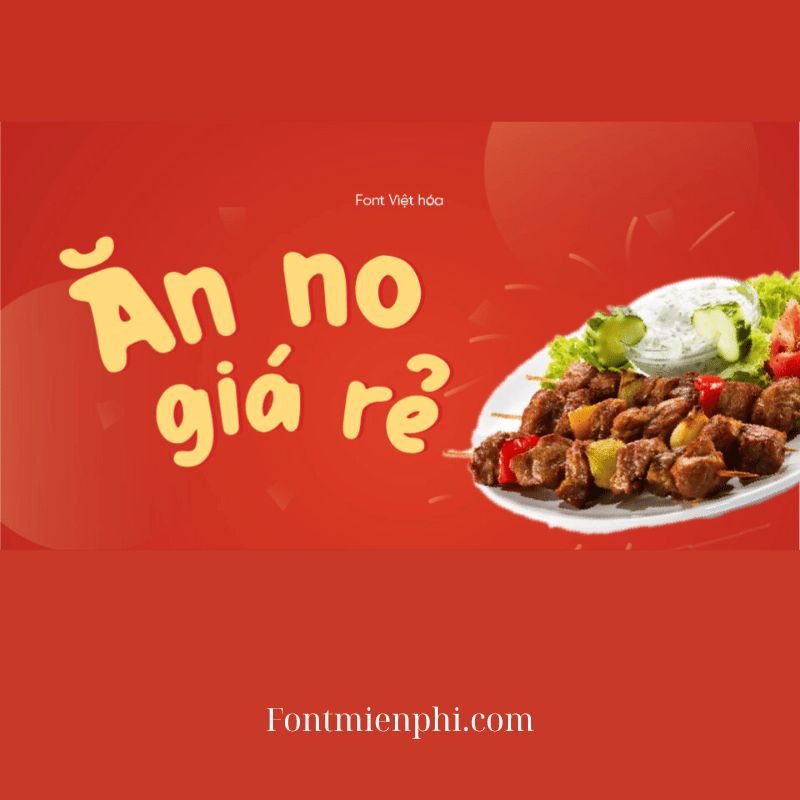
Font Việt hóa 1FTV VIP Red Burger
Font Việt hóa 1FTV VIP Red Burger – Bộ font chữ sáng tạo cho thiết kế ẩm thực
Giới thiệu về bộ Font Việt hóa 1FTV VIP Red Burger
Trong thế giới đồ họa hiện đại, việc lựa chọn Font Miễn Phí phù hợp đóng vai trò quyết định đến sự thành công của một bản thiết kế. Font Việt hóa 1FTV VIP Red Burger là một cái tên nổi bật, mang phong cách trẻ trung và đầy năng lượng. Được lấy cảm hứng từ những tấm biển quảng cáo rực rỡ tại các cửa hàng đồ ăn nhanh, bộ font này mang đến cảm giác ngon miệng và gần gũi ngay từ cái nhìn đầu tiên. Với các đường nét bo tròn mềm mại nhưng vẫn giữ được sự chắc chắn, đây là lựa chọn hàng đầu cho các dự án sáng tạo cần sự phá cách và thu hút thị giác mạnh mẽ.
Đặc điểm nổi bật của Font Việt hóa 1FTV VIP Red Burger
Bộ font này sở hữu bộ ký tự đầy đủ, đặc biệt đã được tối ưu hóa dấu tiếng Việt giúp các bạn học sinh và nhà thiết kế sử dụng mượt mà trên mọi phần mềm. Font Việt hóa 1FTV VIP Red Burger có độ dày nét lớn, cực kỳ phù hợp để làm tiêu đề bài báo, bìa sách giáo khoa hay các poster sự kiện trường học. Sự kết hợp giữa phong cách retro và hiện đại giúp font chữ này không bị lỗi mốt theo thời gian.
Cách ứng dụng Font Việt hóa 1FTV VIP Red Burger hiệu quả
Để tận dụng tối đa vẻ đẹp của bộ font, bạn nên kết hợp chúng với những gam màu nóng như đỏ, vàng hoặc cam.
Sử dụng trong thiết kế đồ họa học đường
Các bạn học sinh có thể dùng font này để trang trí báo tường, làm slide thuyết trình sinh động hoặc thiết kế logo cho câu lạc bộ. Nhờ tính dễ đọc và bắt mắt, thông điệp truyền tải sẽ trở nên ấn tượng hơn bao giờ hết.